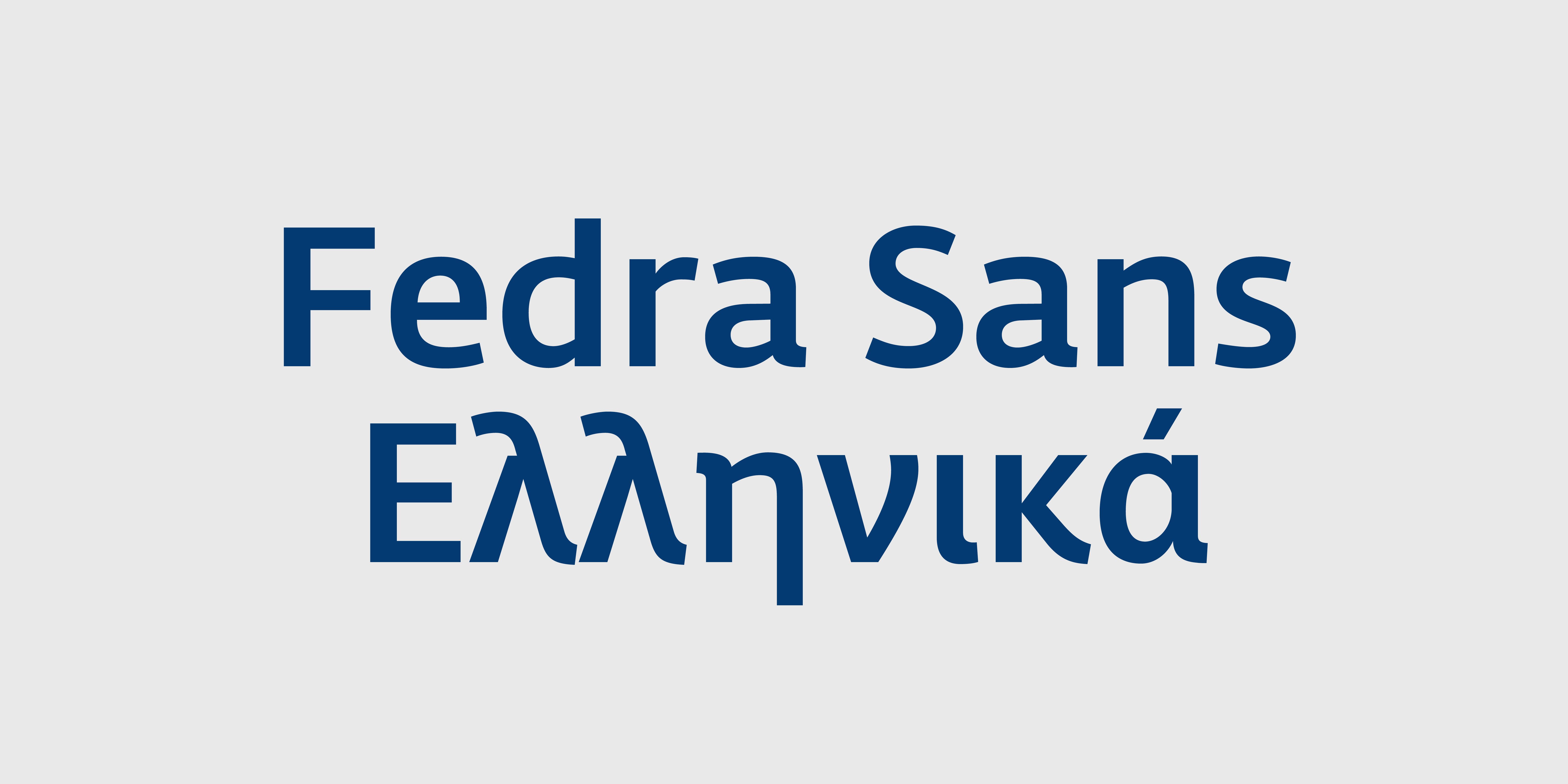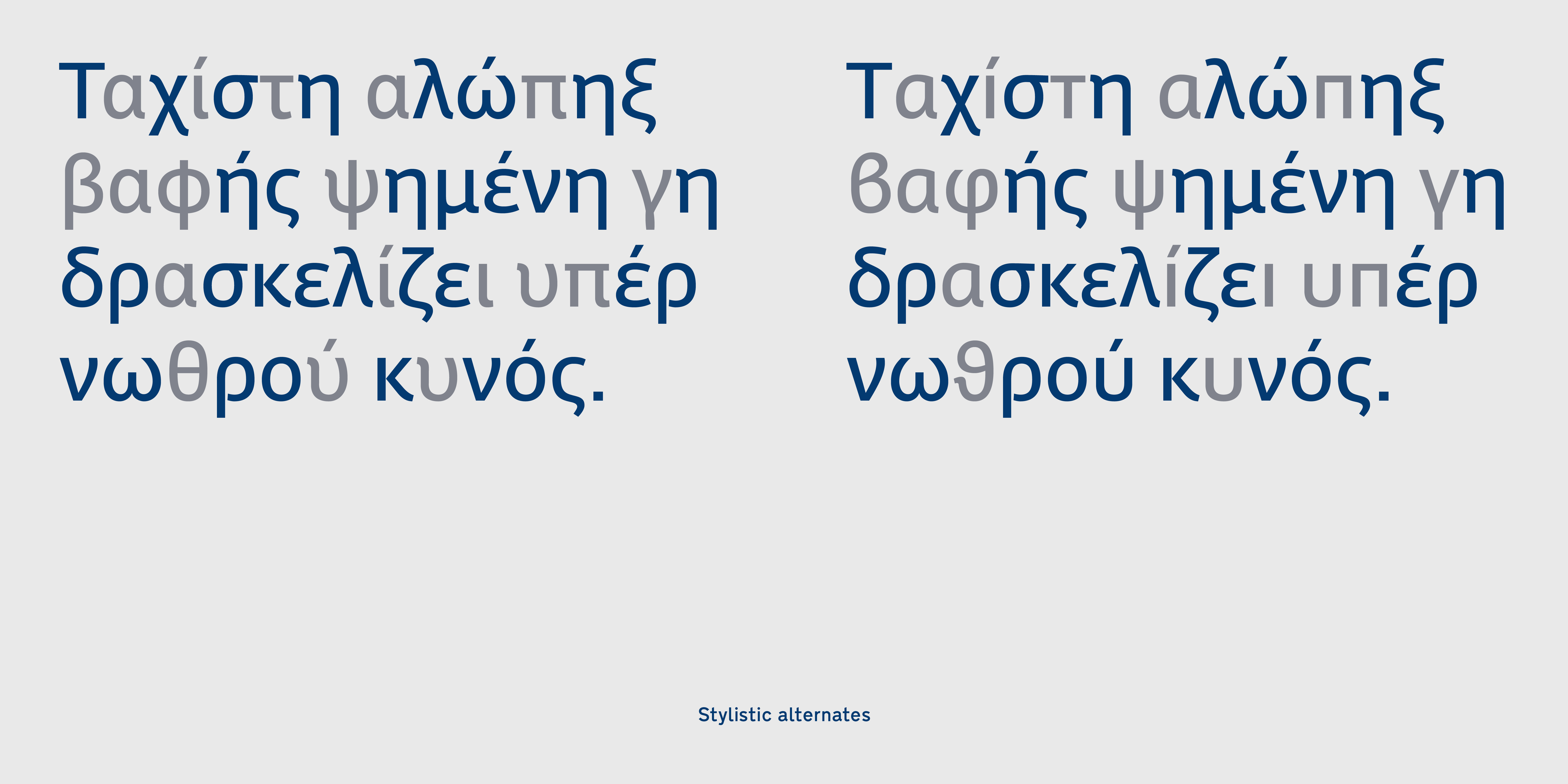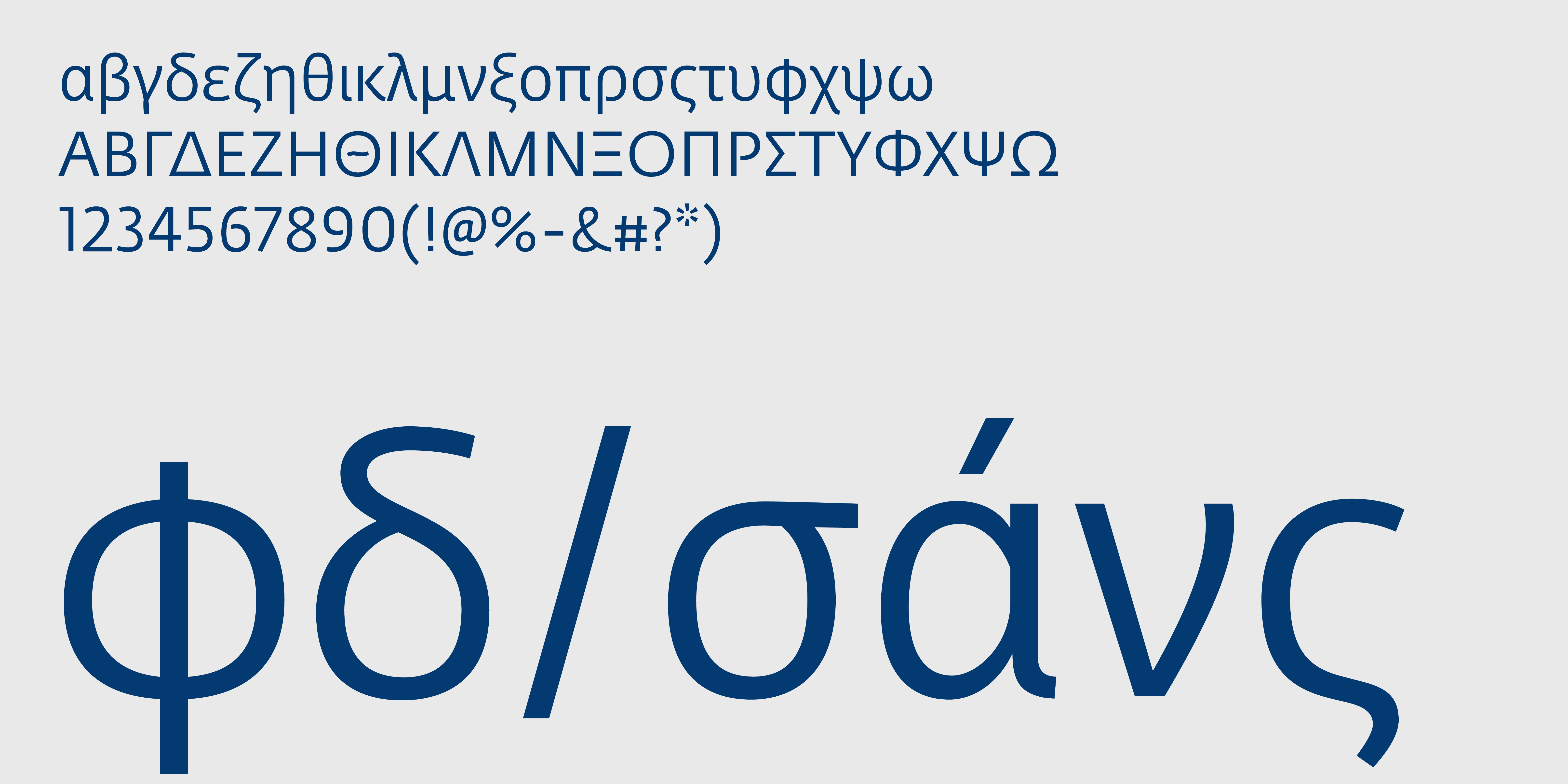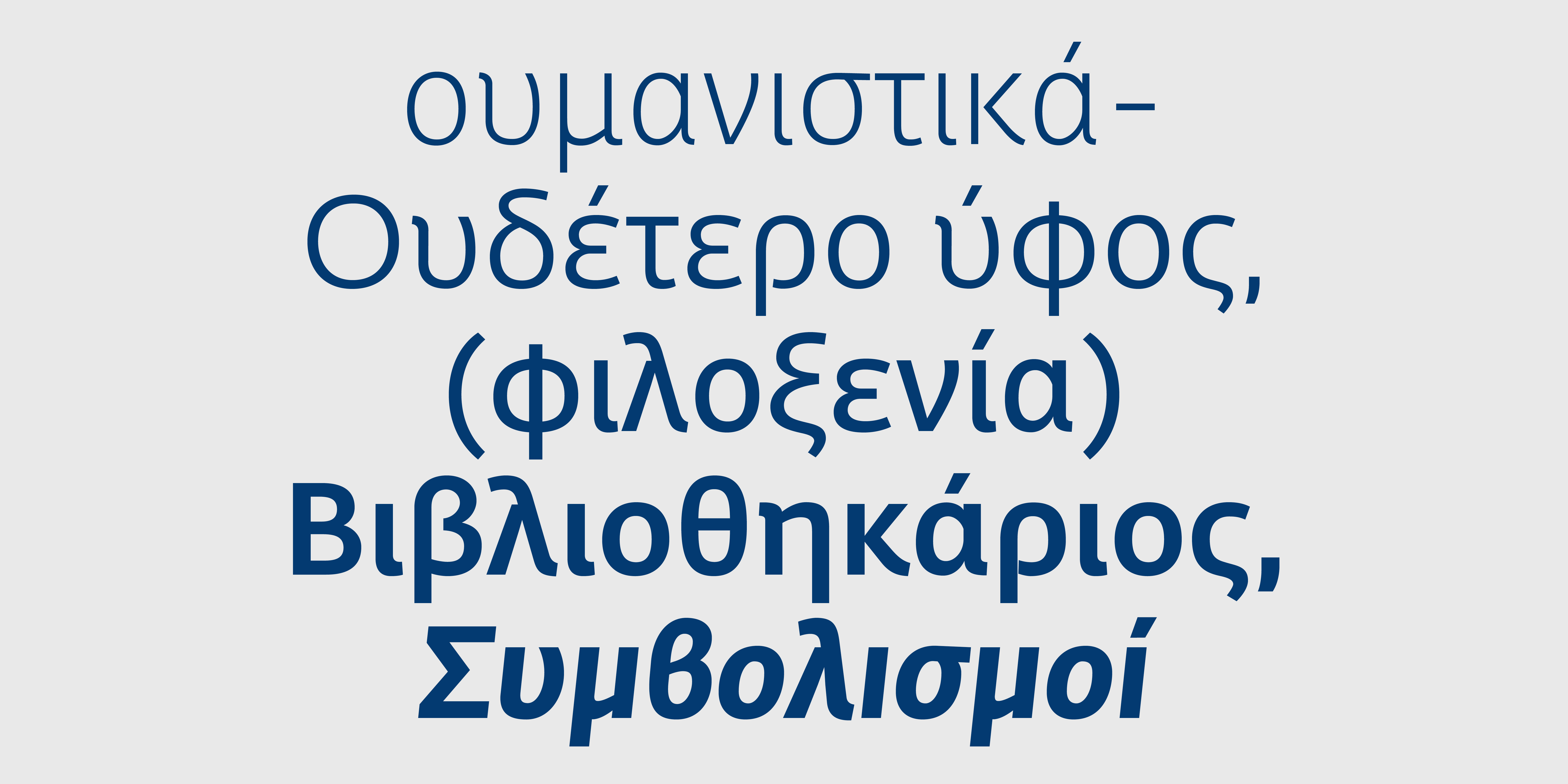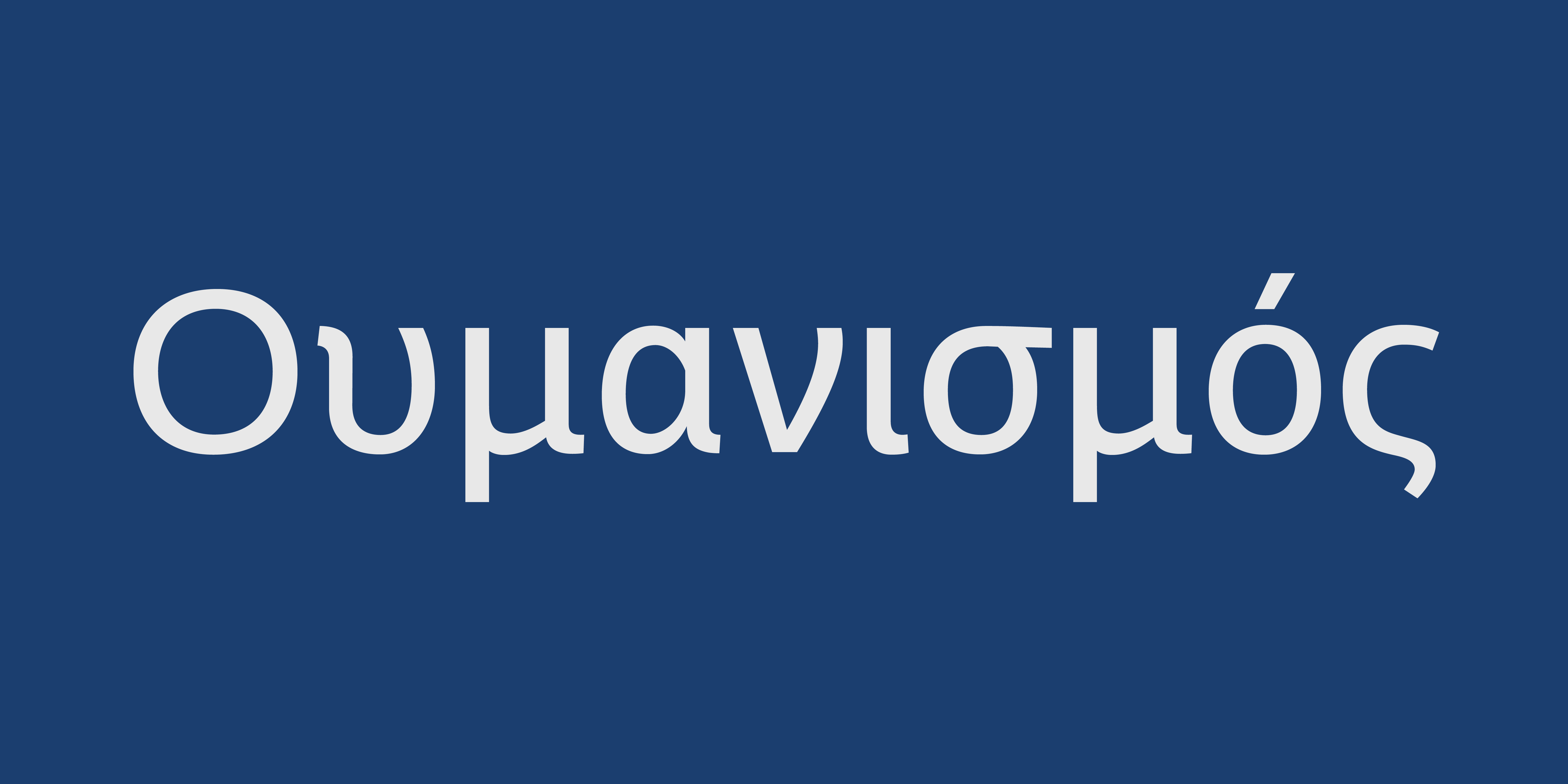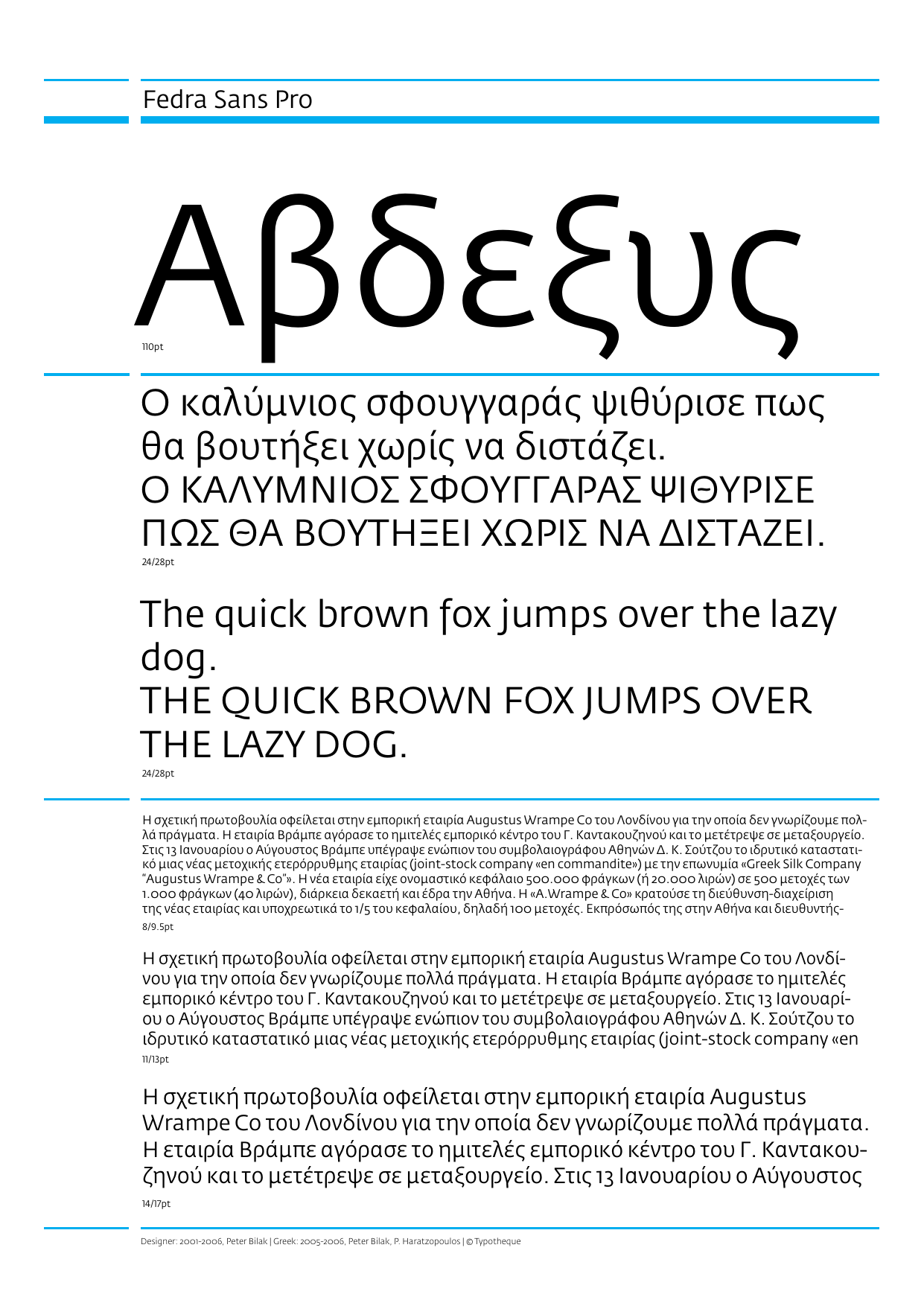
Fedra Sans Pro
Η Fedra Sans ξεκίνησε να σχεδιάζεται ως η εταιρική γραμματοσειρά για την Bayerische Rück, μια γερμανική ασφαλιστική εταιρία, που θα συμπλήρωνε την καινούργια τους εταιρική ταυτότητα. Ο πελάτης όμως εξαγοράστηκε και το σχέδιο για εταιρική γραμματοσειρά εγκαταλήφθηκε. Αφού όμως είχε γίνει ήδη αρκετή δουλειά η γραμματοσειρά ολοκληρώθηκε με την προσθήκη επιπλέον βαρών και ειδικών χαρακτήρων. Είναι μια γραμματοσειρά η οποία να λειτουργεί εξίσου καλά στο χαρτί όσο και στην οθόνη υπολογιστή. Η ελληνική εκδοχή είναι ιδιαίτερα δημοφιλής και χαρακτηρίζει τη γραφιστική δημιουργία στην Ελλάδα τα τελευταία χρόνια. Σχεδιαστής Peter Bilak, Ελληνική έκδοση Παναγιώτης Χαρατζόπουλος.